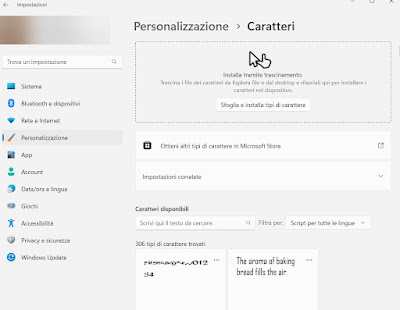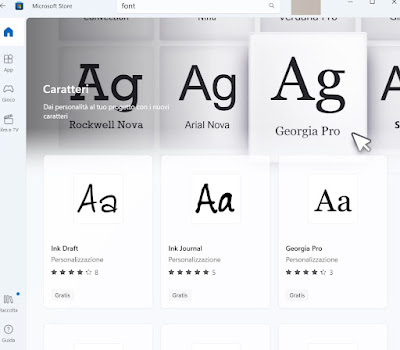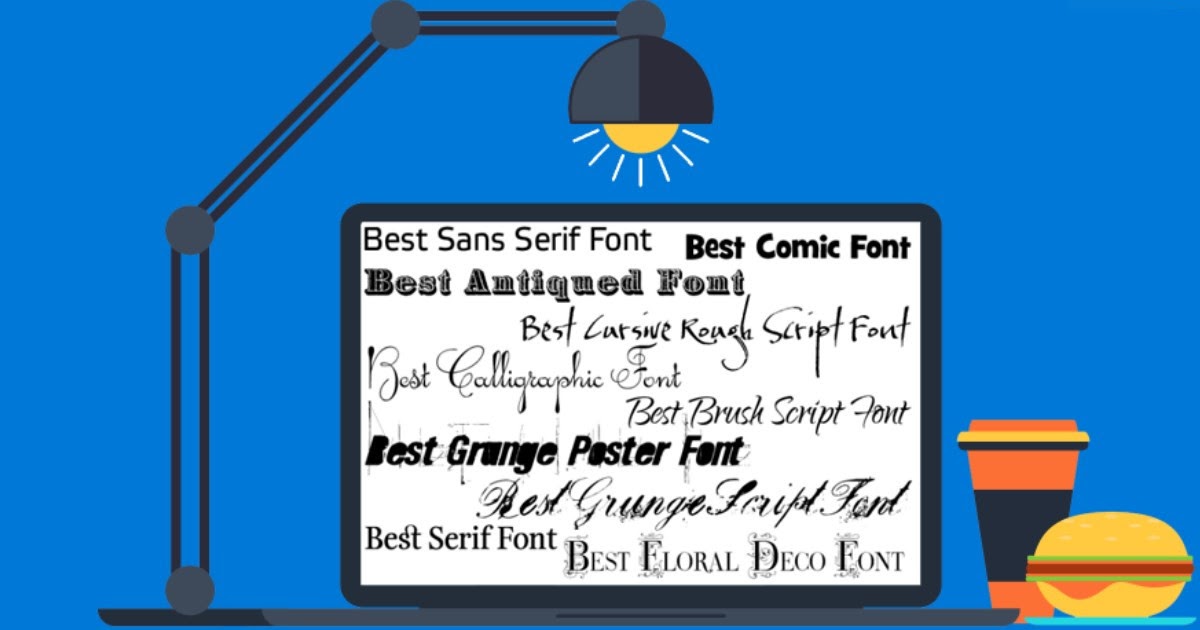
フォントをダウンロードして Windows PC にインストールする方法
Windows 10 と Windows 11 に新しいフォントをインストールするためのガイドと、フォント スタイルを変更するための無料フォントをダウンロードするためのサイト
Windows フォント フォント タイポグラフィーとコンピューターサイエンスの分野では 印刷物や画面上に見える文字の種類. したがって、フォントは私です グラフィック テンプレート たとえば、Microsoft Word などのプログラムでは、便利なドロップダウン メニューから使用するフォントをいつでも選択できるため、作成するドキュメントに最適なテキスト形式を選択できます。
オフィスでは、印刷物や PDF を介して共有される文書にもこのフォントが必要であるため、公式文書用に 1 つの特定のフォントを使用することを余儀なくされることがよくあります (これは非常に専門的でなければなりません)。 これは、フォントが仕事に使用できないという意味ではありません。広告キャンペーンやパーソナライズされたメッセージで使用するために、新しい専用のフォントが作成されることがよくあります。
私たちも同じテキストの単調さを変えたい場合は、このガイドでその方法を紹介します。 Windows に新しいフォントをインストールする、だからから ユニークでパーソナライズされた文章でコンピューターにドキュメントやシートを書く、特にドキュメントを作成して共有する場合は特に美しいです。
同じ画面で、ストアからではなく他のサイトからダウンロードした場合は、フォント ファイルを破線のボックスにドラッグして、新しいフォントをインストールすることができます。 ただし、インストールされているフォントの 1 つをクリックすると、そのフォントをアンインストールしてコンピューターから削除することができます。
同じページからアイテムをクリックできます Microsoft Store で他のフォントを入手する、Microsoft 自体が提供するフォントをダウンロードするため。 新しいフォントを広範囲に探したくない場合は、ストアから入手できるフォントで解決することもできます.
4) フォントでインクを節約する
毎日多くのドキュメントを印刷すれば、 安価なフォントを使用して印刷プロセスでインクを節約する、これは、微視的なレベルで各文字のインク使用量が少ないことを意味します。
Microsoft Word でインクを節約するには、文字とフォントを使用することをお勧めします ガラモンドだけでなく、時代を超越した タイムズ ニュー ローマン またはフォント ゲージ 彼らは自分自身をよく守ります。
ワードフォント 可能であれば、次のようなフォントは避けてください。 アリアル、 ヴェルダナ、コミック サンズ と 影響、捨てるインクがたくさんない限り!
ドキュメントを印刷するときにインクを節約するには、ガイドをお読みください。 ドキュメントの印刷時に保存するフォント と インクとプリンターのカートリッジを節約する.
結論
フォントのインストールと変更は非常に簡単な操作です Windows で行う必要があり、適切な練習をすれば、重要なドキュメントを印刷する必要があるときや、陽気で楽しいフォントを使用したいとき (特に招待状やカードを作成する場合) に、フォントをすばやく変更できます。